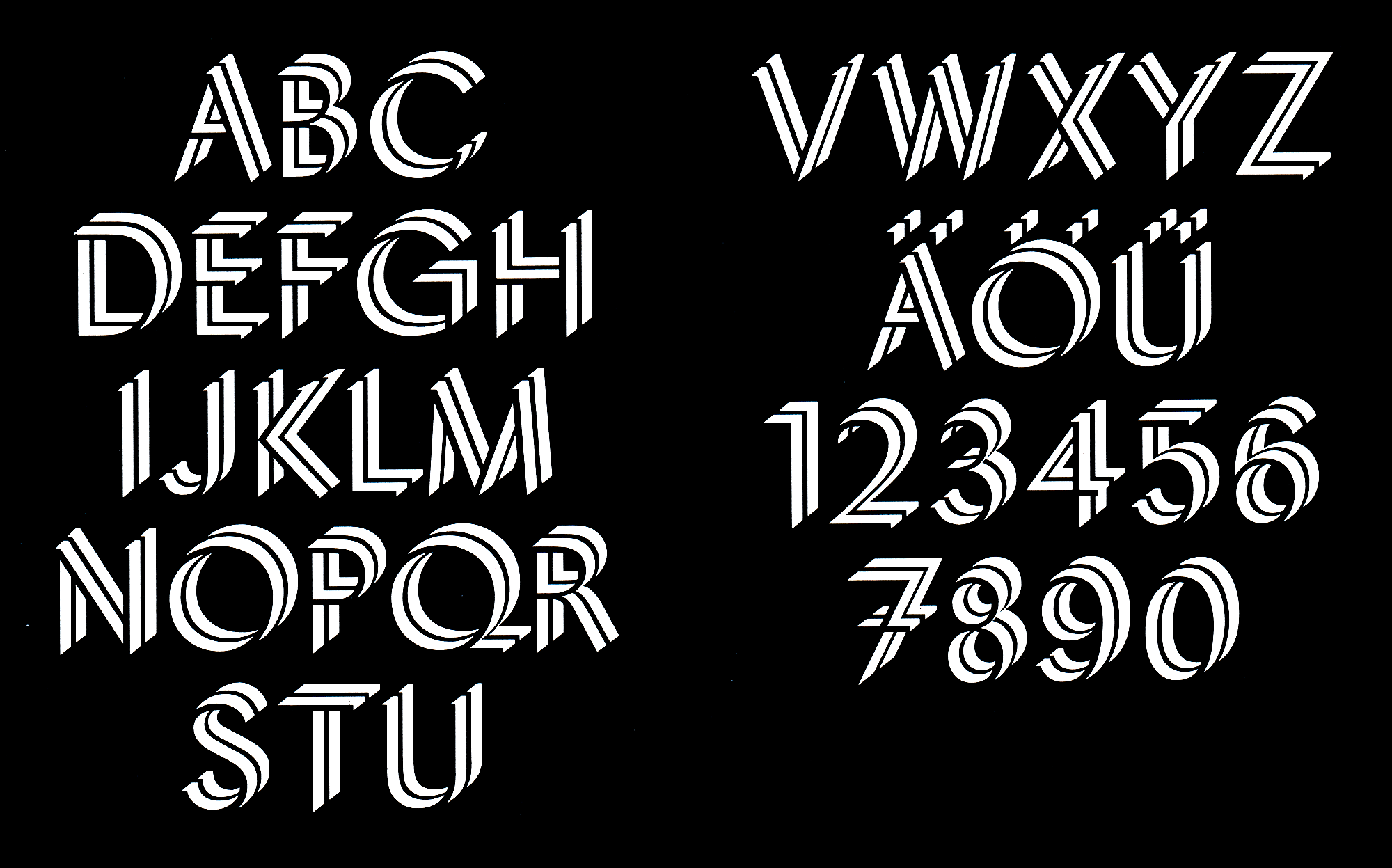
Font-Wiki: Biga
• circa 1989
• Antiqua dekorativ
Für die Biga erhielt Fritz Richter anlässlich des Ideenwettbewerbes um neue Auszeichnungsschriften 1985 den 2. Preis. Die Biga wurde mit einer zugehörigen Schrift vorgelegt, bei der die Teilung der Grundstriche fehlt. Typoart entschied sich wegen des interessanten Effektes für die vorrangige Einführung der Biga. Die Veröffentlichung erfolgte gemäß verschiedener Sekundärquellen um 1989.
Die Schrift wurde über Elsner+Flake in einem Schaugrößenschnitt digital verfügbar gemacht (»TH-Garnitur«).